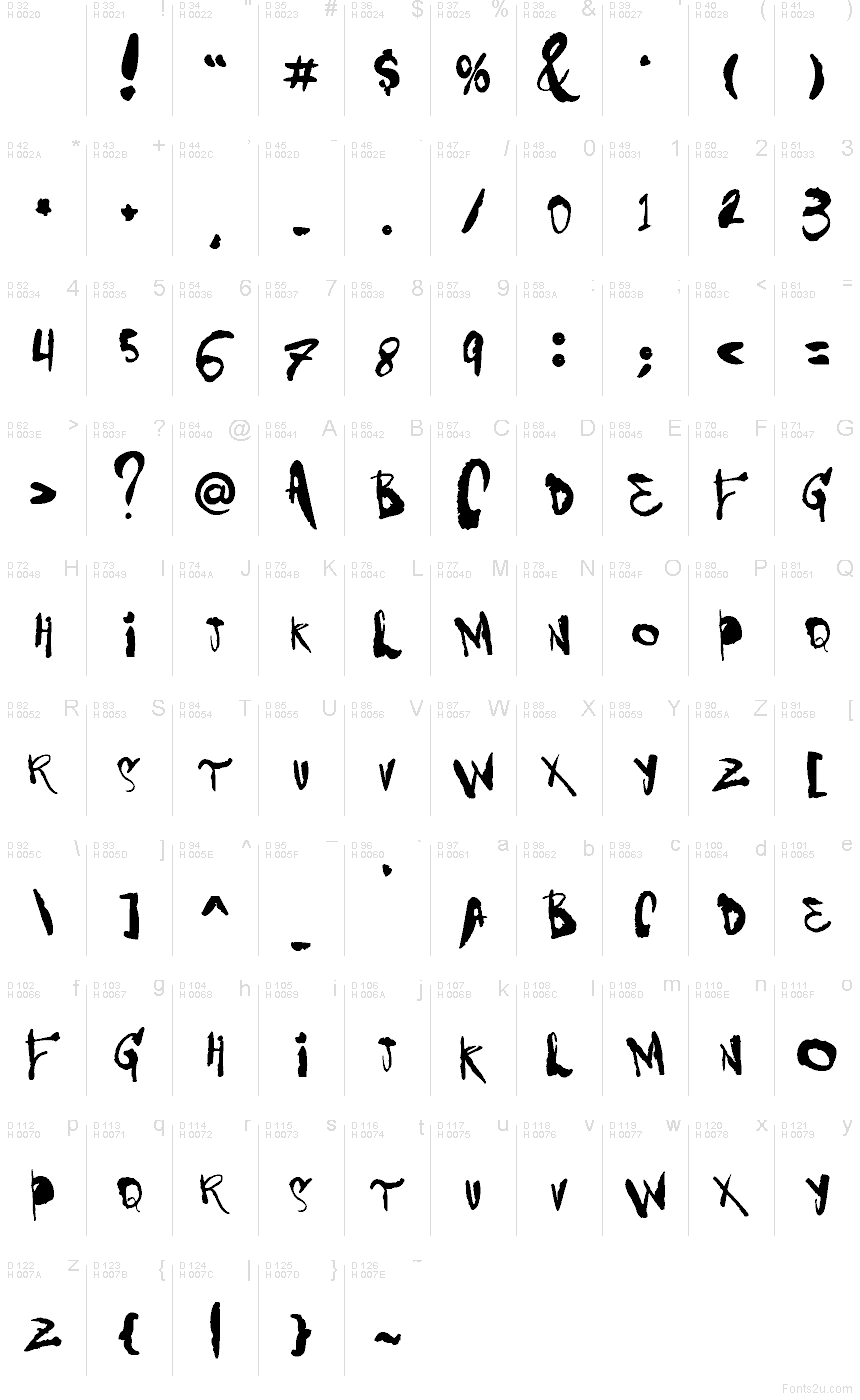
VTKS DENGOSA Regular
VTKS DENGOSA - це безкоштовний графіті-шрифт у стилі brush, що вирізняється різкими змінами силуету: від щільних, насичених фарбою мазків до тонких, чіпких ліній, схожих на швидкий слід маркера. Цей нерівний ритм надає літерам енергію вуличного теггінгу. Завдяки бризкам, заломам та потовщеним кінцям шрифт виглядає по-справжньому живо і спонтанно, на відміну від нудних, «вилизаних» накреслень.
Музичні флаєри, скейтерська графіка, заголовки плакатів, обкладинки альбомів та мерч - це ідеальне застосування для VTKS DENGOSA, особливо якщо потрібен ефект «брудного» хендстайлу, а не акуратний шрифт для оформлення. Рваний слід пензля відмінно впишеться в зіни, наклейки та графіку для соцмереж, де сира текстура працює значно ефективніше, ніж вивірені до ідеалу форми.